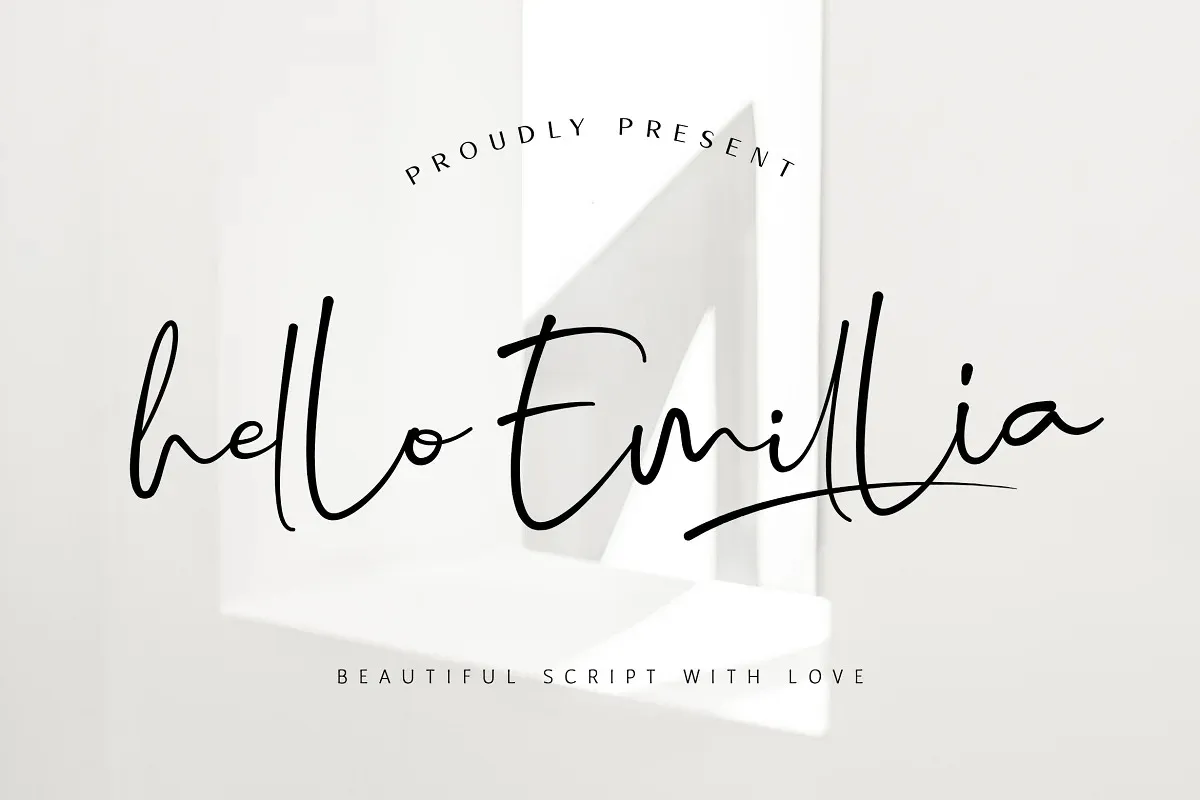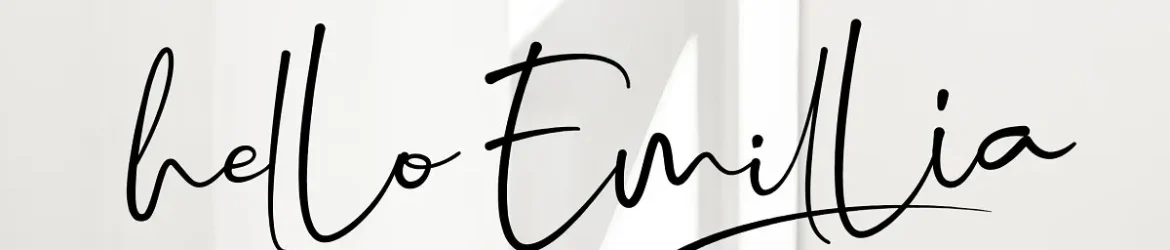
A Hello Emillia é uma deliciosa seleção de tipo de mão escrita para quem busca algo que seja tanto criativo quanto confortável de se usar. Embora a descrição original sugira um tom chique e elegante, sua natureza descontraída e acolhedora torna-a perfeita para designers que valorizam uma mistura de estilo casual e formal em seus projetos. Ideal para quem busca uma fonte única e versátil para trabalhos como cartas pessoais, assinaturas e design gráfico minimalista, a Hello Emillia oferece tanto um toque sofisticado quanto um ar descontraído que pode deixar seu trabalho ainda mais personalizado e cativante. Seja você designer de moda ou web, criador de conteúdo online, ou simplesmente quem busca uma fonte única para seus projetos pessoais, a Hello Emillia é uma ótima escolha.